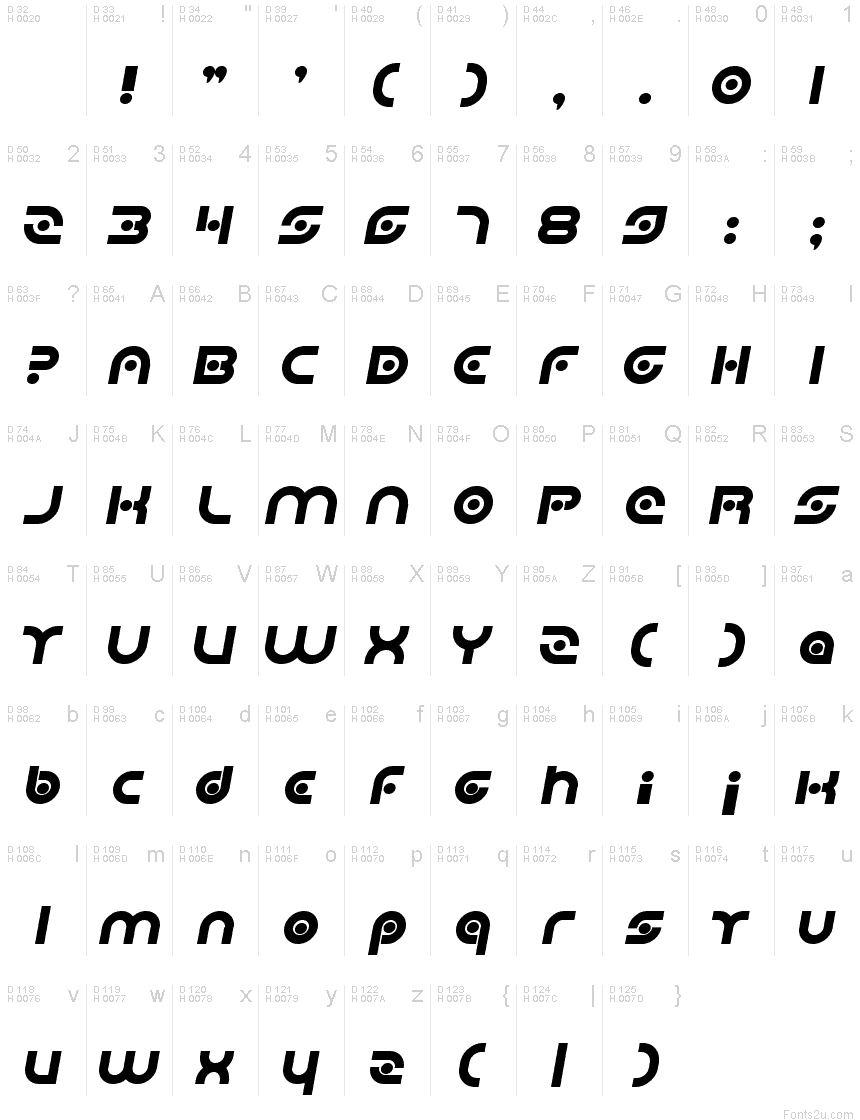
Planetary Orbiter Bold Italic, stworzony przez ShyWedge w 1999 roku, to darmowy, retro-futurystyczny font typu display z wyraźnym klimatem epoki kosmicznej. Grube, zaokrąglone litery pochylają się do przodu niczym w starych logotypach science-fiction, a powtarzające się koliste wycięcia i pierścieniowe formy nadają alfabetowi orbitalny, mechaniczny rytm, żywcem wyjęty z kieszonkowej fantastyki naukowej i technologicznych wizji końca XX wieku.
Dzięki temu font ten naturalnie pasuje do tytułów na plakatach, logotypów gier, okładek albumów, ulotek klubowych i plansz tytułowych, gdzie potrzebny jest darmowy krój z wyraźnie kosmicznym nastrojem. Sprawdza się również w krótkim brandingu, zapowiedziach na okładkach czasopism i efektownych nagłówkach, ponieważ pochylenie i powtarzający się motyw okręgu nadają mu charakteru niemal bez ingerencji projektanta.
Planetary Orbiter
Planetary Orbiter SF
Planetary Orbiter Bold Italic